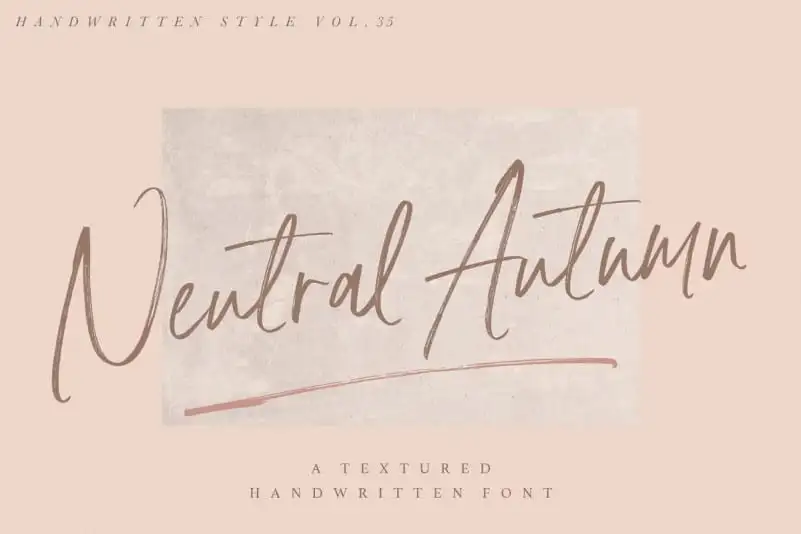
Neutral Autumn Brush Font – Download Grátis
A Neutral Autumn Brush Font é uma opção ideal para quem busca uma fonte script com uma aparência natural e envolvente. Com seu aspecto casual mas bem formado, esta tipografia oferece um tom neutro que promete melhorar a legibilidade dos seus materiais digitais. Além disso, sua leveza de tinta característica, combinada com algumas alternativas minúsculas e ligaturas, recria uma sensação natural de escrita à mão, fazendo desta uma excelente escolha para qualquer projeto que deseja um toque de sofisticação e autenticidade. Essas características fazem da Neutral Autumn Brush Font um recurso indispensável para designers em 99designs, capaz de trazer vida aos seus projetos com um design cuidadosamente balanceado entre simplicidade e personalização.